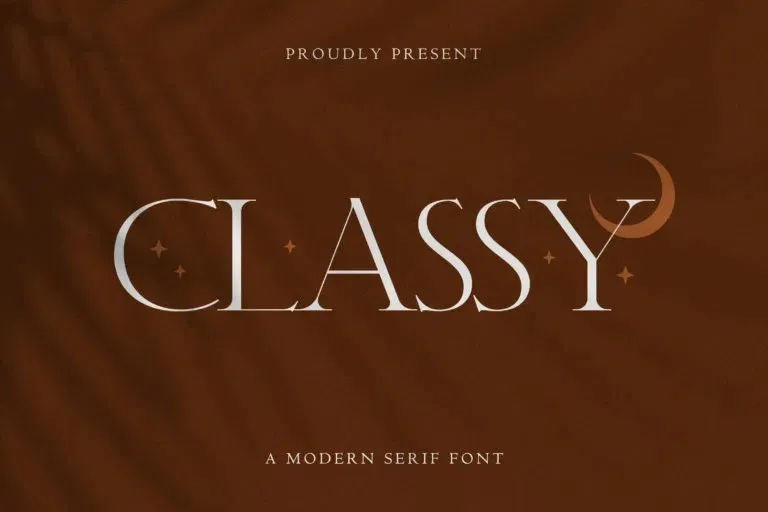
Classy Font é uma elegante e fina fonte serif que oferece um toque de sofisticação para seus projetos digitais. Fabricada pela Typefactory, essa tipografia não apenas adicionará um ar de sofisticação a qualquer projeto gráfico, mas também o dará aquele ar final perfeito. Confortável tanto para leitura quanto para uso em aplicações visuais como identidades visuais de marca, cartões de apresentação, rótulos e até mesmo logotipos, essa fonte oferece uma ampla gama de possibilidades. Não importa qual categoria de trabalho você está lidando, a Classy Font é certamente uma escolha versátil e perfeita para qualquer necessidade de design. Além disso, a capacidade de se adaptar a diferentes fins de uso como cartas de viagem, placas de sinalização ou até mesmo selos e bandejas, faz dela uma fonte indispensável em seu arsenal de ferramentas gráficas.